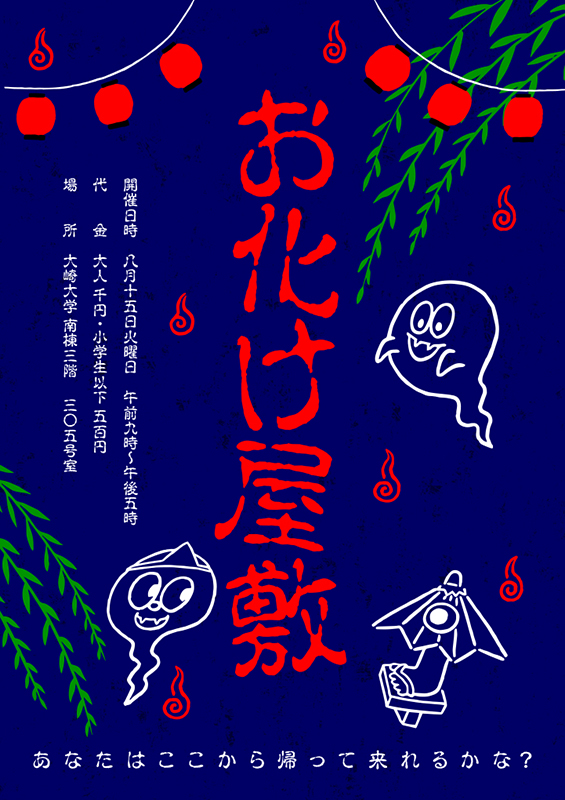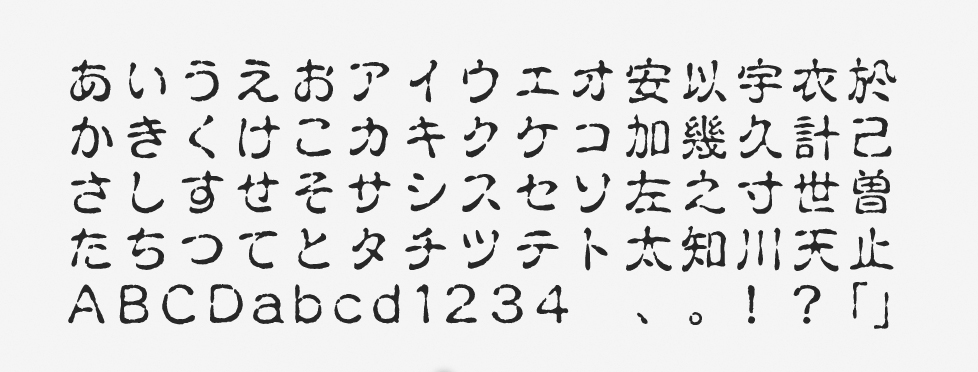
「TB古印体」について
古印体は、奈良時代の寺社で使用されていた印鑑の書体がもとになっています。複製されにくい特徴があるため、現代でも電子印鑑などに活用されることは多いです。モリサワが取り扱っているTB古印体は、古印体をベースにしつつも古めかしい印象を払拭することを目指し、現代風にアレンジされています。
「TB古印体」の特徴
特徴的な切欠部では、石に彫られた文字の一部が欠けて生じる形が再現されています。自然でアクのない処理を施し、 “偶然の妙” を表現していることが特徴です。筆勢や筆の強弱も、自然に引き立つように設計されています。
おどろおどろしい雰囲気があるため、お化け・幽霊なども含めたホラーにまつわるデザインに最適です。現代風にアレンジはされていますが、ベースは古印体であるため、通常の明朝体やゴシック体と比べれば時代性も表現できます。
線が均一でなかったり、途中で途切れたりしているため、一見「怖い」印象が強いフォントです。怖さを感じさせるシーンと合わせて、やはり古印体がベースであるため、歴史を感じさせるような場面でも有効でしょう。特にコミックなどで効果的に使われています。